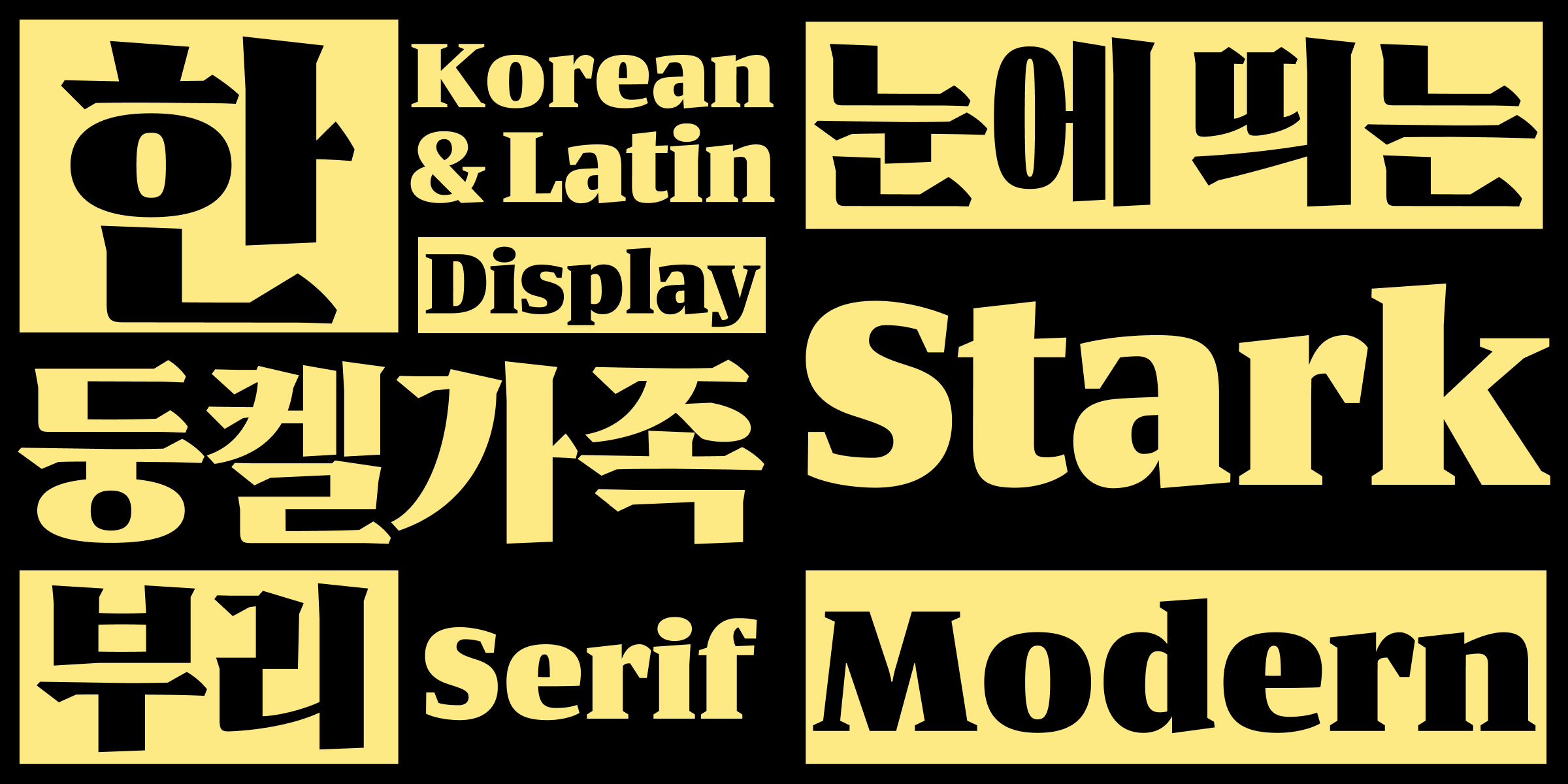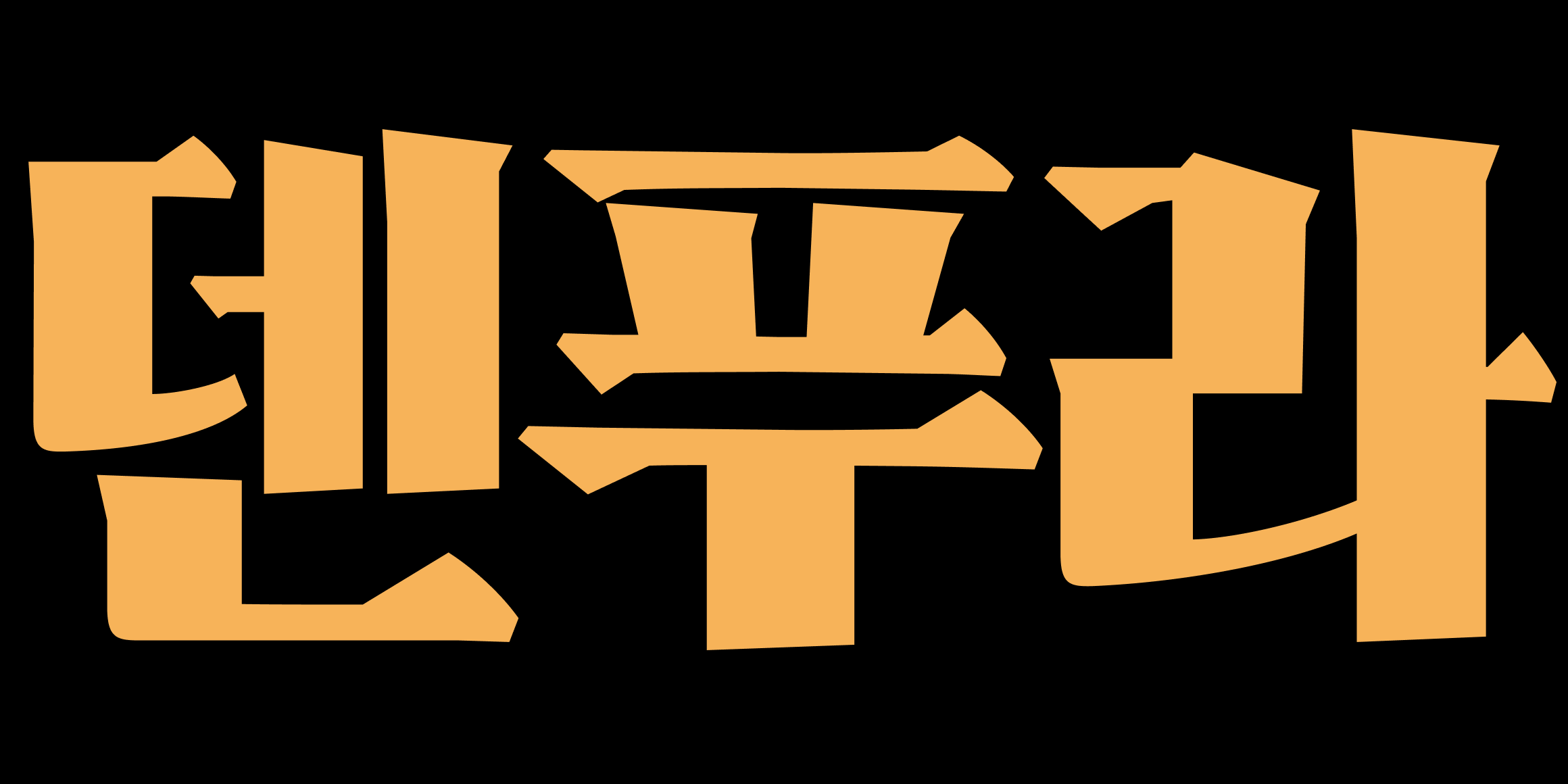
둥켈세리프
둥켈세리프는 획이 굵고, 대비가 커서 눈에 띄는 디자인의 글자체입니다. 가는 획이 단단해서 작은 크기에서도 비슷한 계열의 다른 글꼴보다 잘 보이며 견고한 텍스트 질감을 갖고 있습니다. 둥켈세리프의 라틴은 함민주가 시작하고 마크 프롬베르크가 다듬고 완성도를 높여 함께 진행했습니다. 포스터, 책, 썸네일 제목, 패키지 디자인 등에 사용해 보시길 추천합니다.